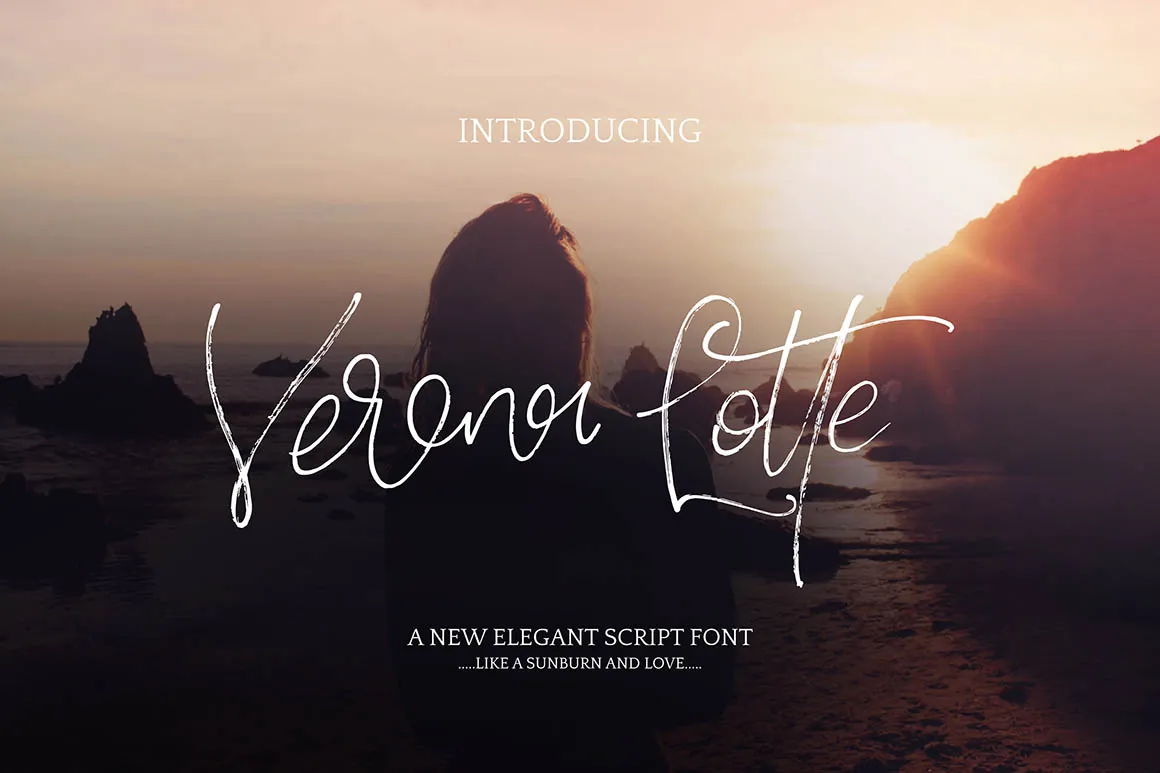
Verona Lotte Script Font – Download Grátis
Através do trabalho meticuloso do designer Yasir Ekinci, chegamos à Verona Lotte Script Font, uma elegante tipografia desenhada para ser brilhantemente manipulável com mãos. Esta fonte é um belo exemplo de tipo a mão, criado para fornecer suporte linguístico completo e perfeitamente acessível. Seu design único é ideal para diversos usos, desde assinaturas de logotipos até cardapios em restaurantes ou cartões de visita e convites para casamentos. É uma fonte vibrante, adequada tanto para a web quanto para o papel, prometendo dar um toque especial a qualquer projeto que você decida aplicar. Seja para assinaturas sofisticadas ou criações criativas, Verona Lotte é uma escolha excepcional em nosso catálogo de fontes Brush Fonts.